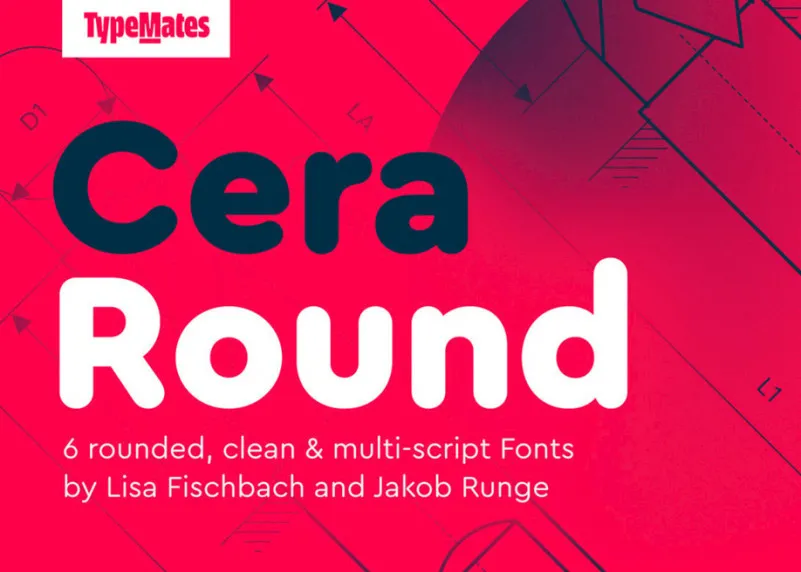
Esta é uma família moderna de fontes livresiras. É perfeitamente adequada para todas as iniciativas criativas. Ela tornará cada projeto mais fácil e mais divertido. Introduzimos a Cera Round Pro Sans Serif Family ! Ela foi projetada por Jakob Runge, Lisa Fischbach e publicada pela TypeMates. Contém seis estilos e opções de pacotes familiares. Como qualquer outro membro do catálogo, ela combina uma calidez com elegância e seu suporte para cirílico e grego a torna uma companheira fiável e atraente para comunicação internacional. Esta fonte é certamente algo que vai adicionar estilo e conforto ao seu próximo projeto.